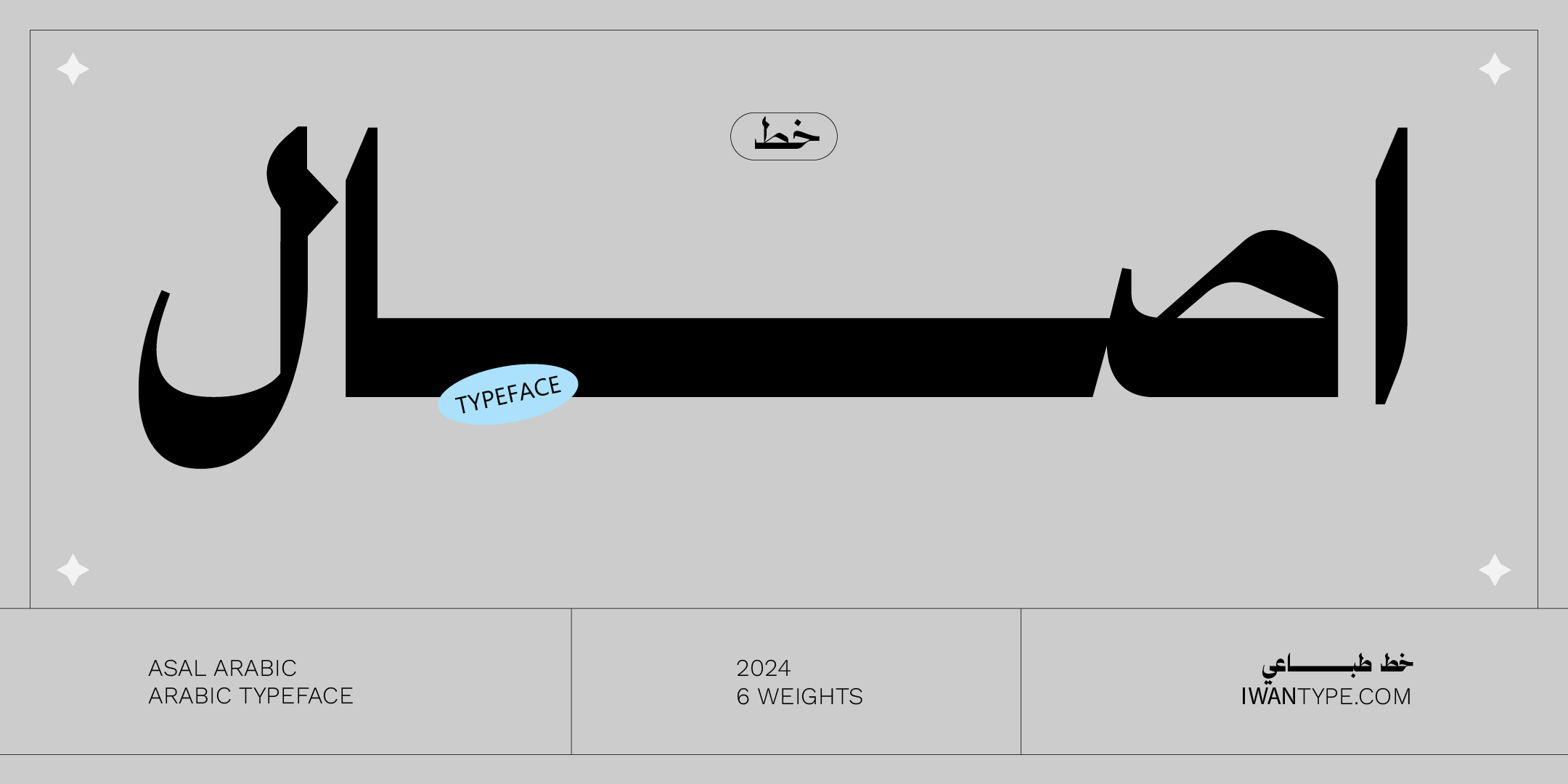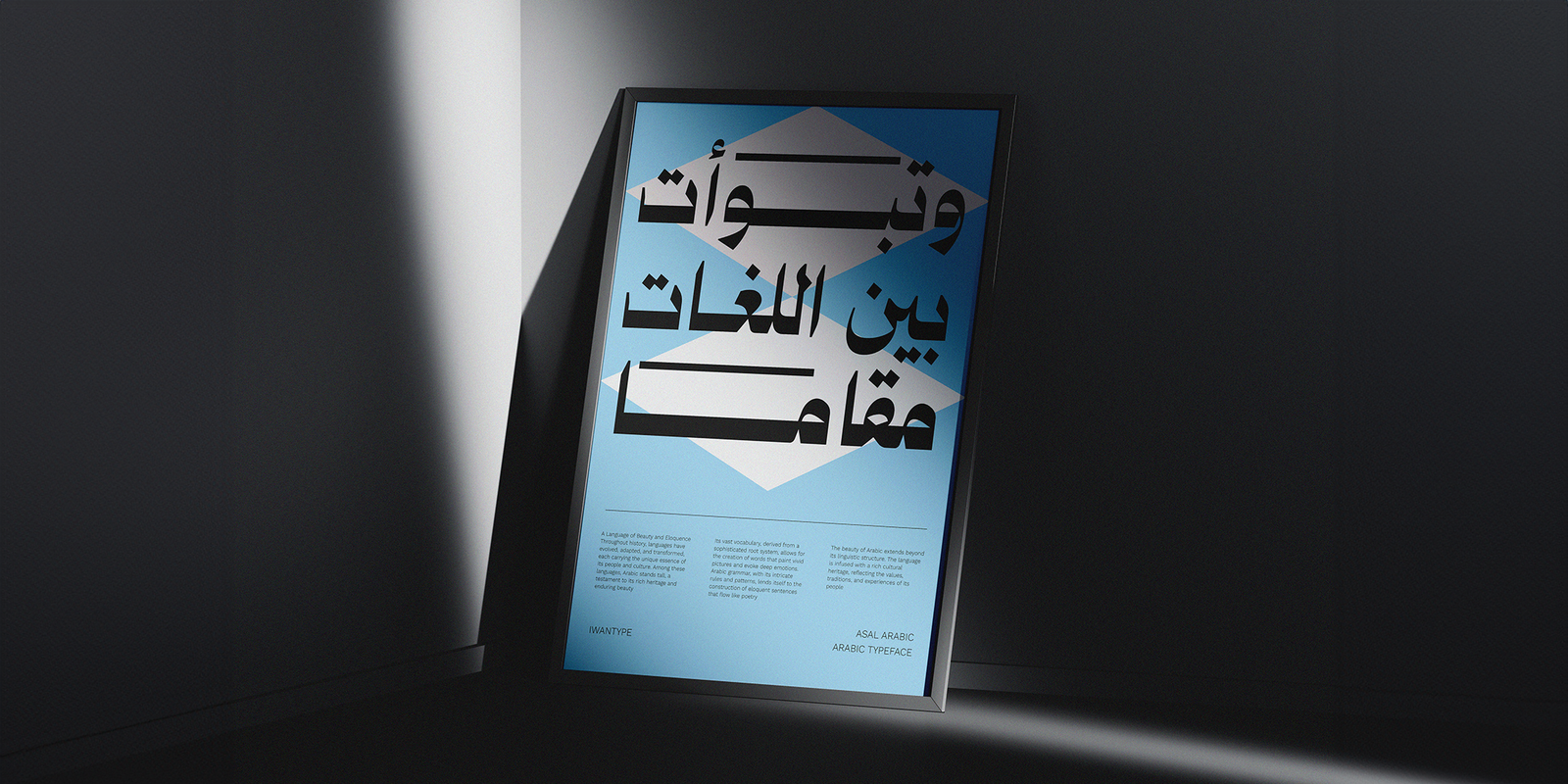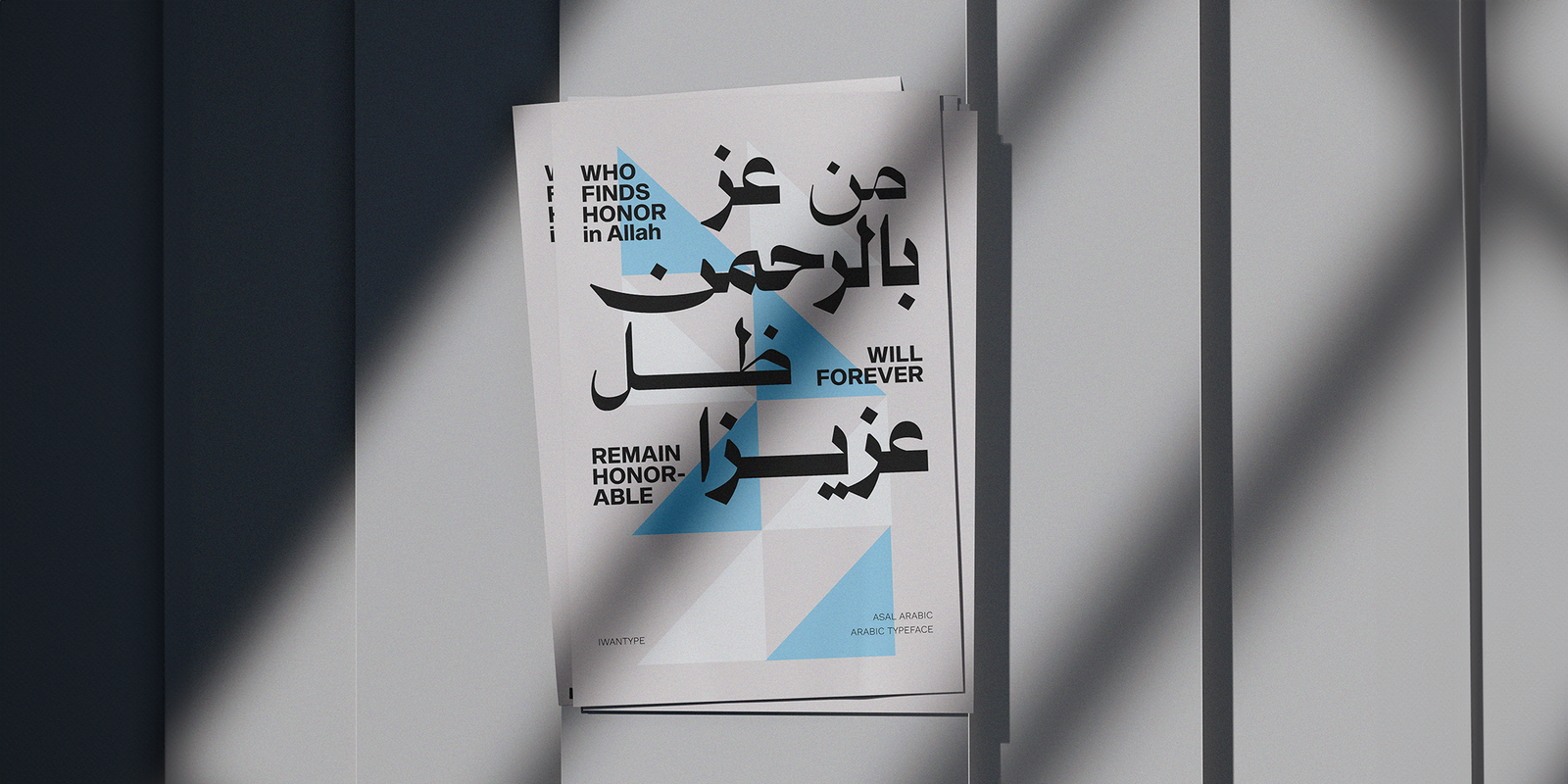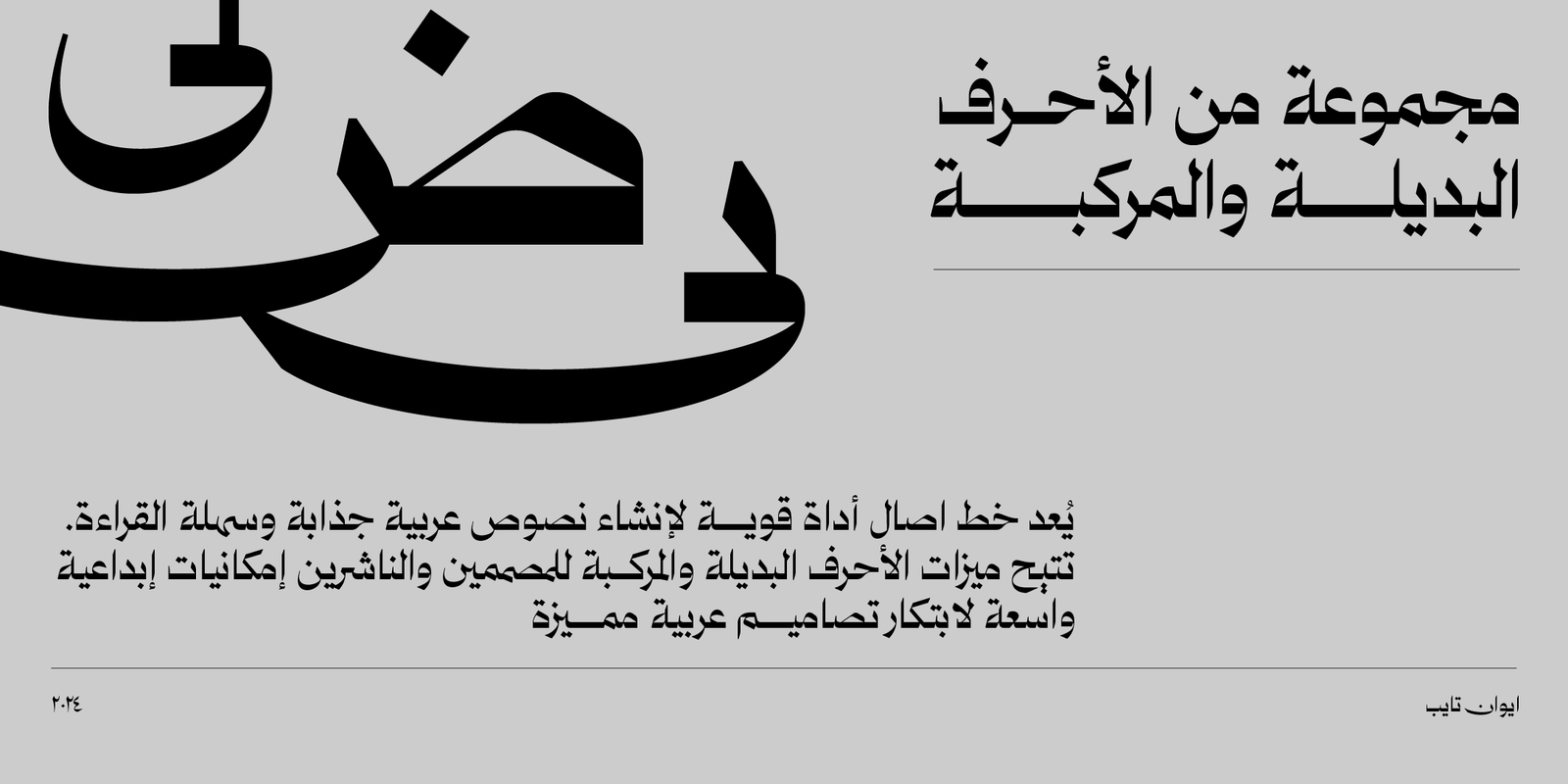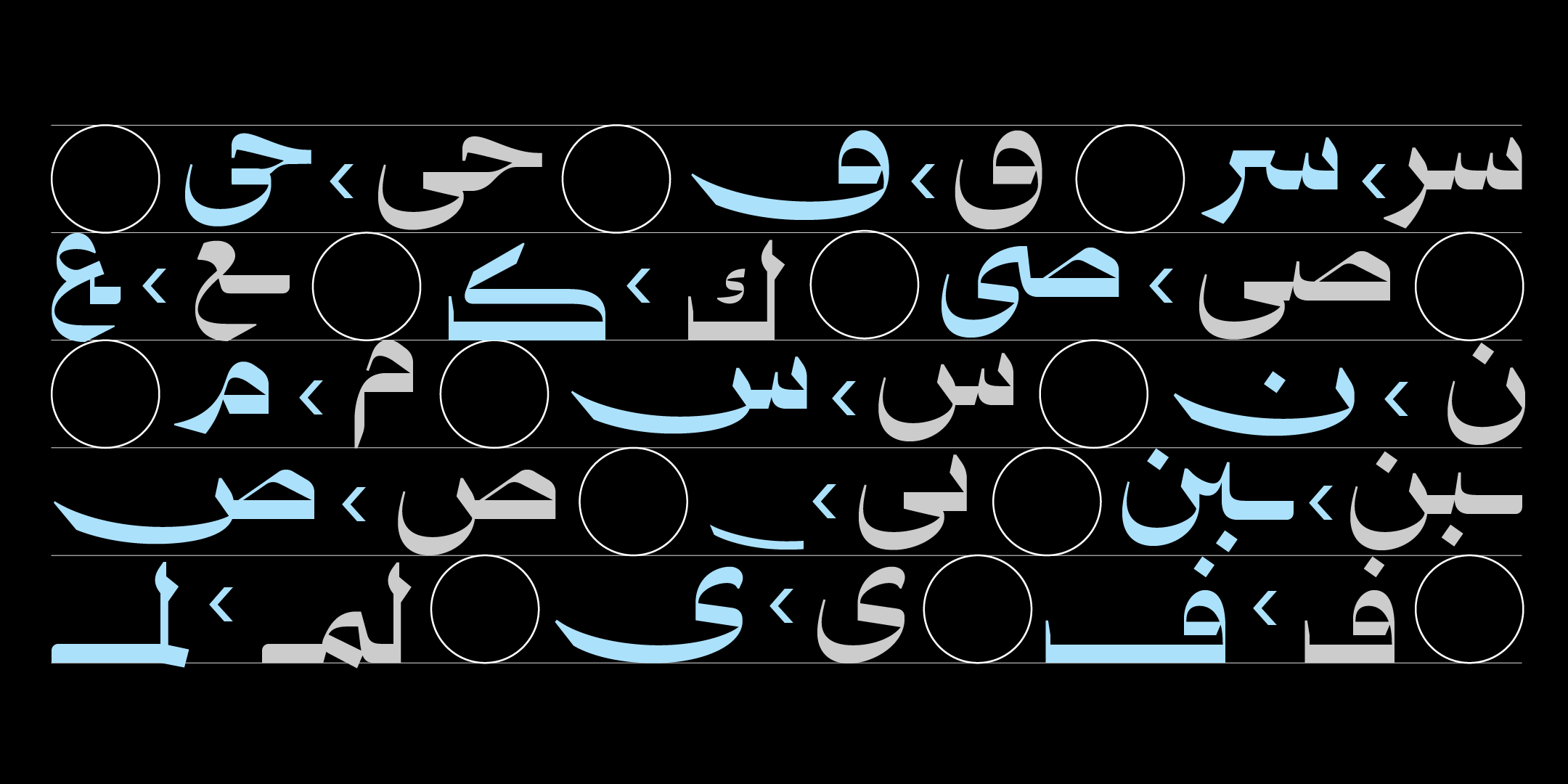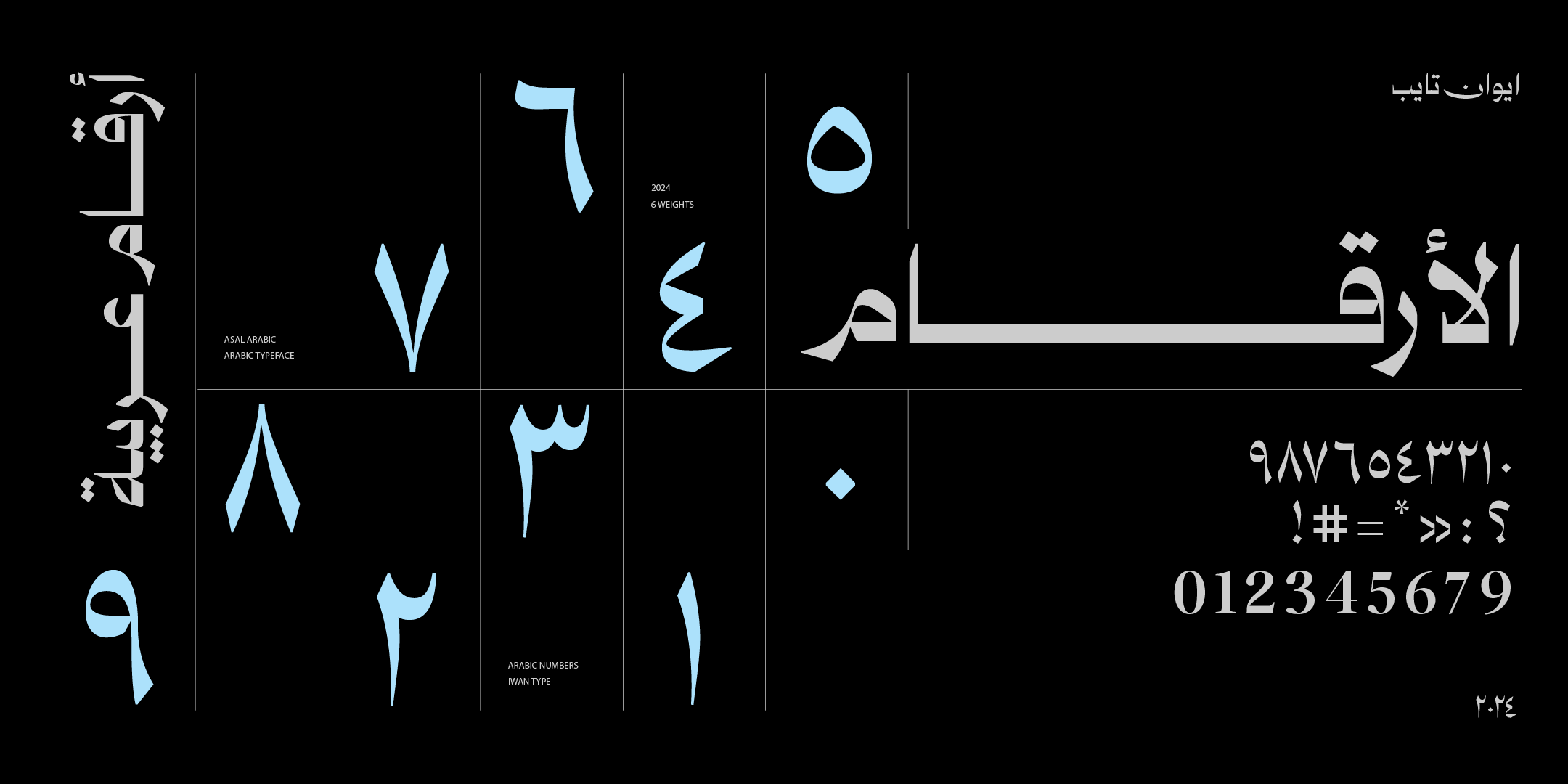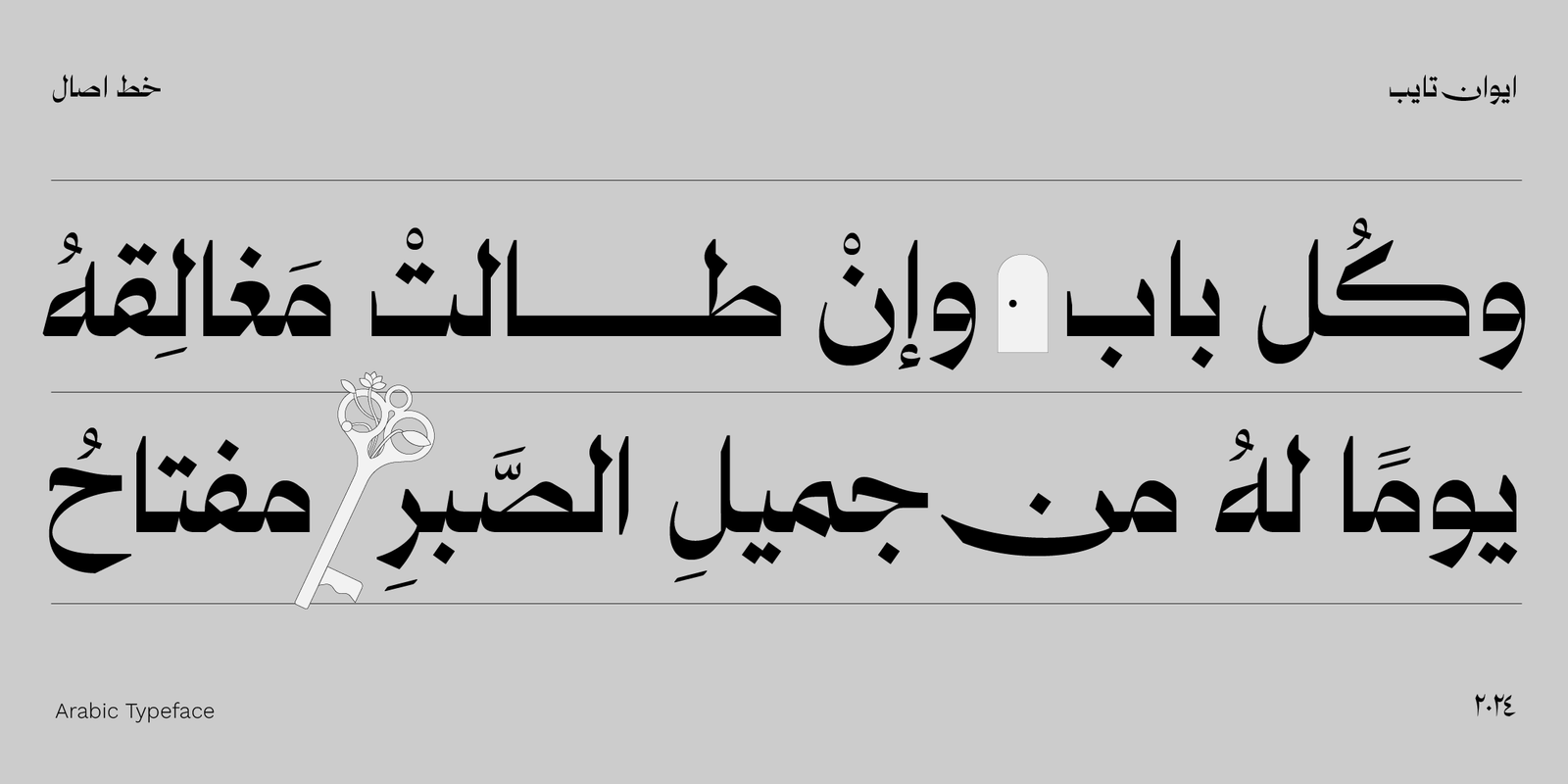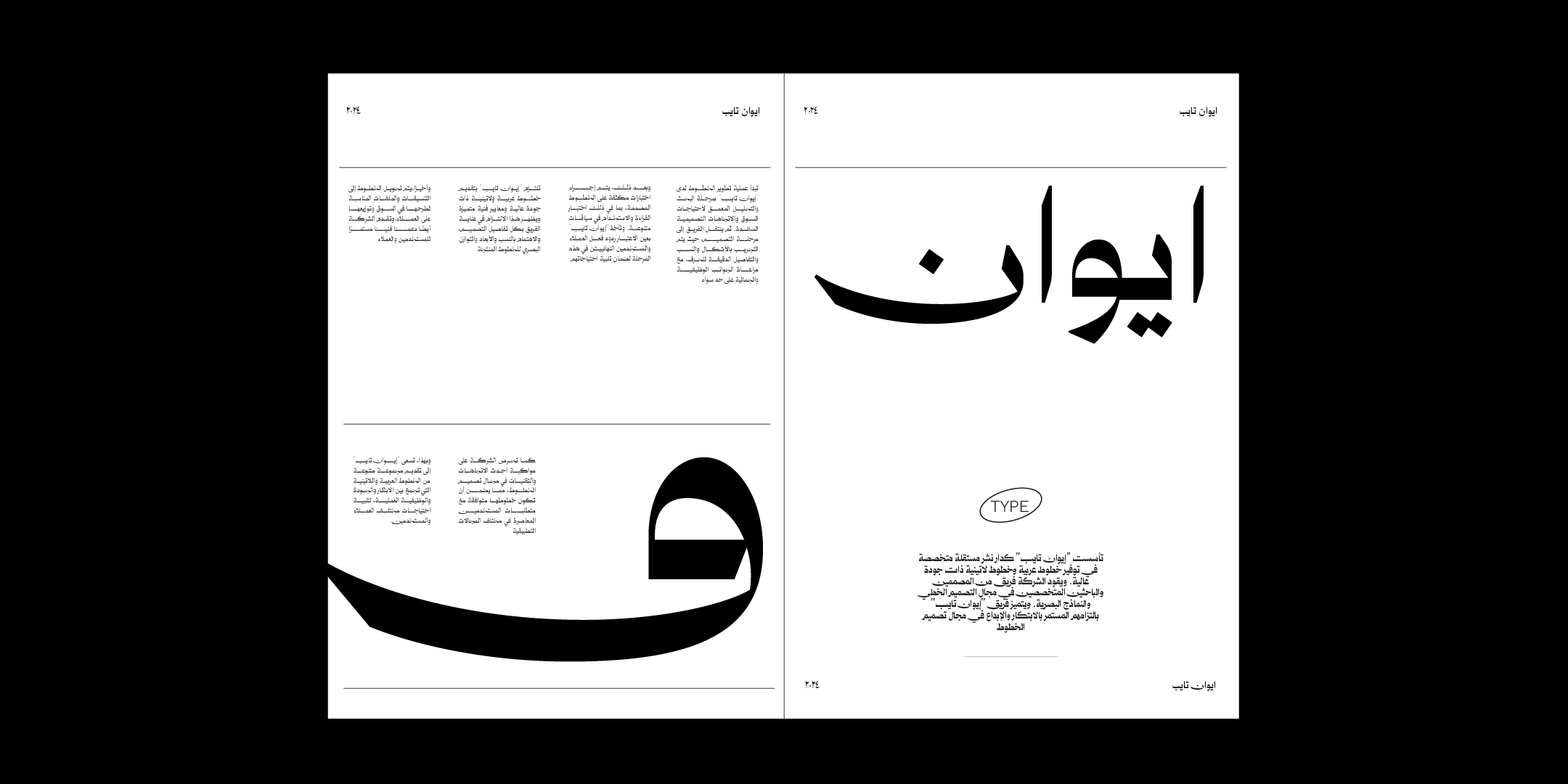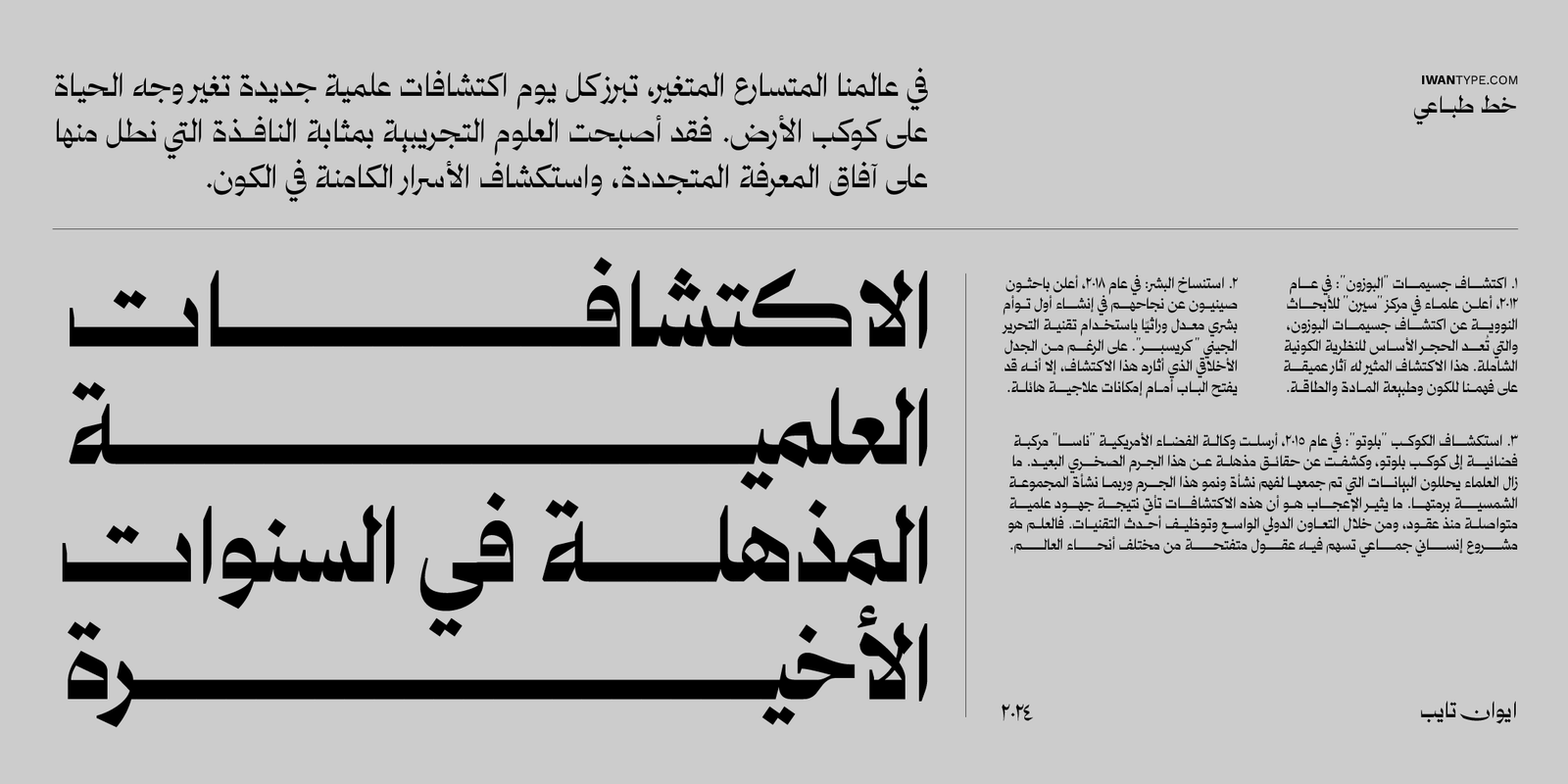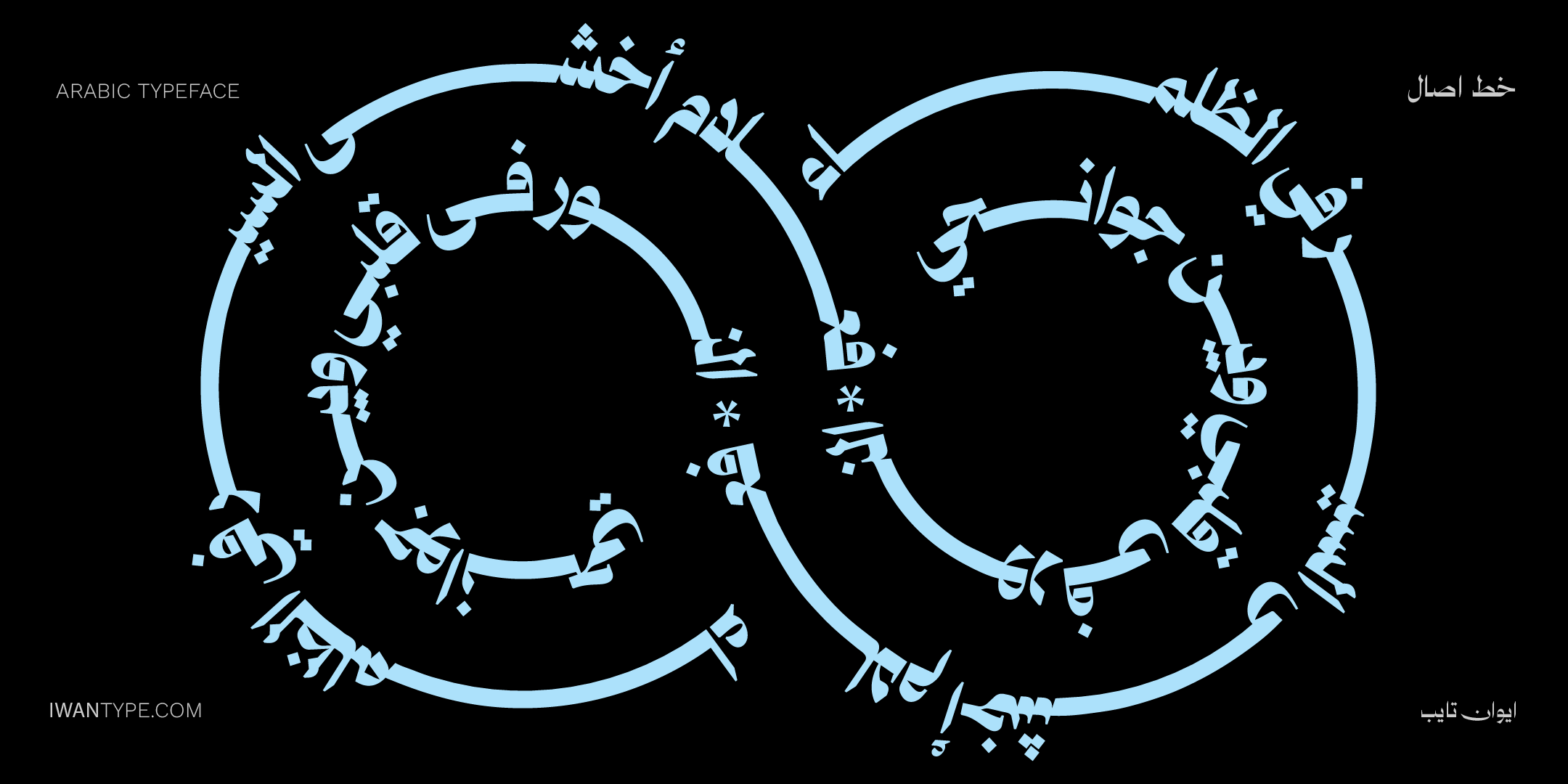
خط اصال عربي – Asal Arabic Typeface
خط أصال عربي – Asal Arabic Typeface
أصال هو خط طباعي عربي يجمع بين التقليد والحداثة بأناقة فريدة. يتميز بتصميمه الأنيق واستخدامه للخطوط الهندسية، مما يضفي عليه طابعًا مميزًا وجذابًا. يتضمن ميزات أوبن تايب مثل الحروف البديلة والحروف المركبة، مما يتيح للمستخدمين تجربة متميزة في التصميم العربي.
Asal Arabic Typeface
Asal Arabic is an Arabic typeface that elegantly blends tradition with modernity. It stands out with its sleek design and use of geometric lines, giving it a distinctive and appealing character. Featuring opentype functionalities such as alternate glyphs and ligatures, it offers users a unique experience in Arabic typography.
اللغات: العربية فقط، بلا حروف لاتينية
الاوزان : 6 اوزان